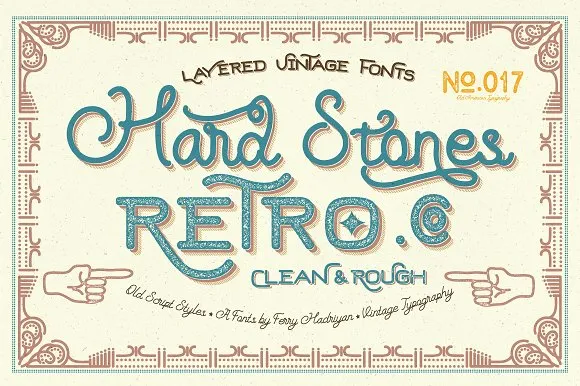
Através de feydesign chegamos a Hard Stones Sans Strip Font, uma nova opção no universo das fuentes de exibição. Esta fonte é parte do rico catálogo de sans-serif, display e script desenvolvido pela Hamilton. Com um design que combina modernidade com um toque vintage, ela se destaca por seu estilo autêntico, sem a necessidade de muito esforço na montagem da tipografia. Perfect para vários usos visuais, essa fonte é ideal para design de elementos, eventos, camisetas, logotipos, moedas, adesivos e criações incríveis em geral. Ela possui um estilo limpo e rústico, tornando-a uma excelente escolha para quem procura algo único que se destaque na tela ou no papel. Hard Stones Sans Strip é a fonte perfeita para aqueles buscando um novo toque moderno e vintage com um toque de rusticidade exuberante.